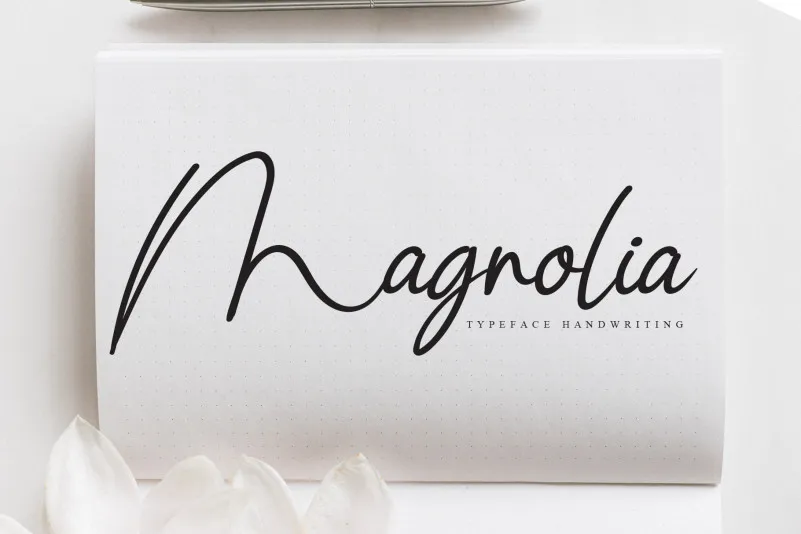
Magnolia Script Font – Download Grátis
Magnolia Script Font é uma elegante e clássica fónt que se destaca pela sua escrita calligrafia. Embora seja conhecida principalmente para seu uso em design gráfico, esta fonte também brilha quando usada em anúncios de casamento, cartões de agradecimento, citações e cartas de boas-vindas. Suas formas delicadas e suaves são perfeitas para dar um toque personalizado às suas criações digitais. Com Magnolia Script Font, você pode criar trabalhos que não apenas destacam seu trabalho, mas também oferecem uma sensação encantadora de autenticidade e afeto ao mesmo tempo. Seja para cartões de boas-vindas criativos ou design de logotipos exclusivos, esta fonte é um maravilhoso complemento para qualquer designer gráfico que procura adicionar uma pitada de seriedade às suas criações.